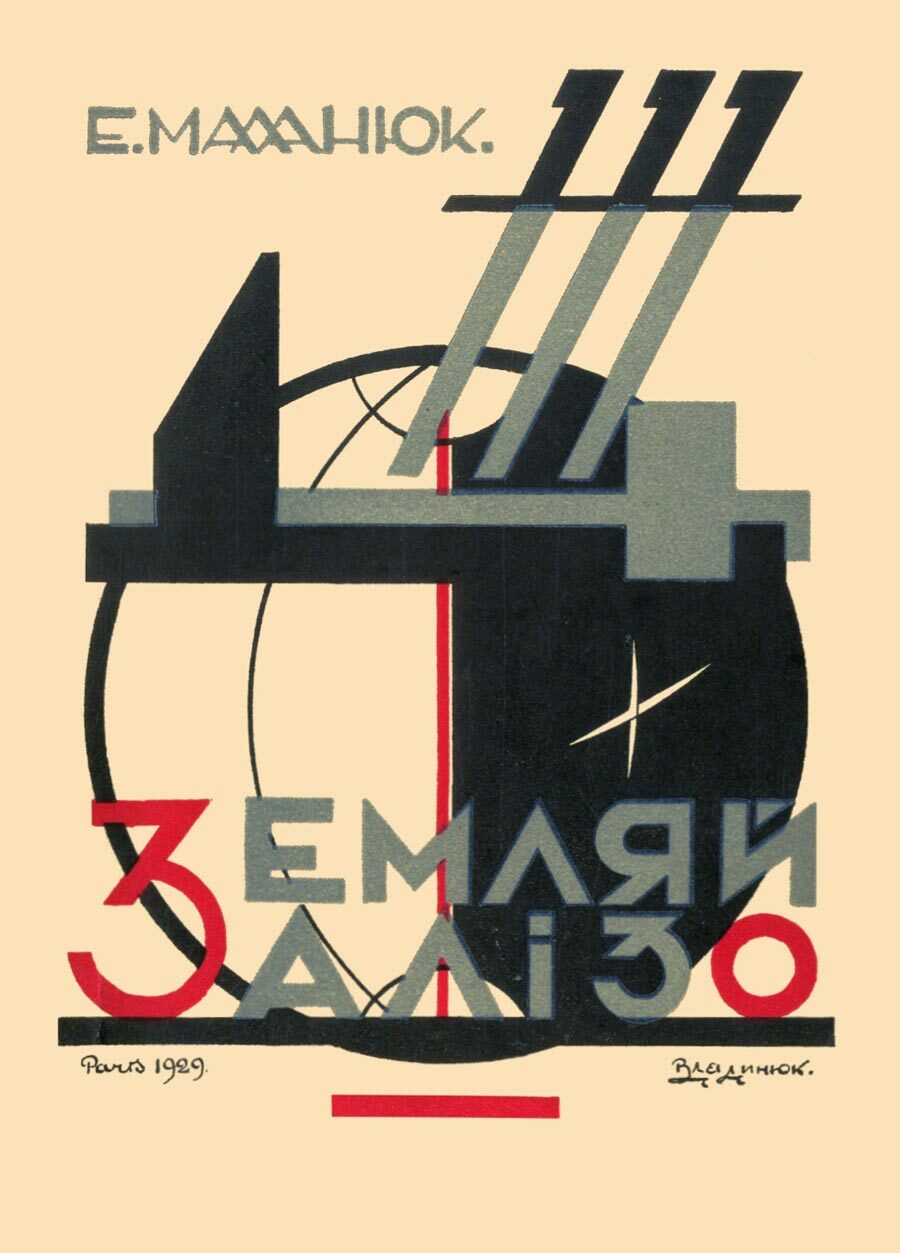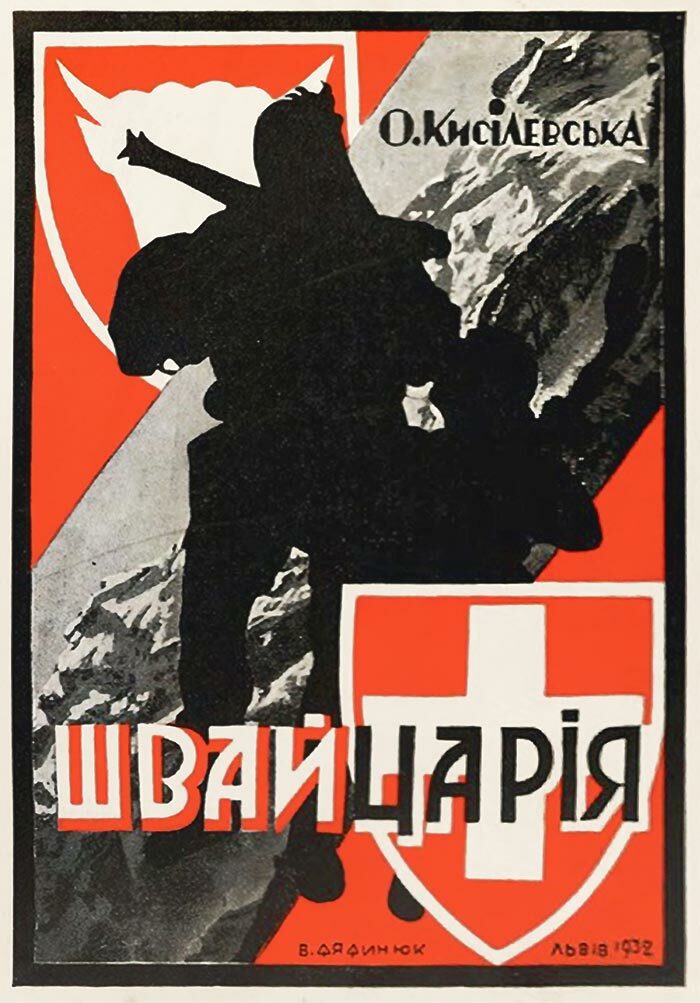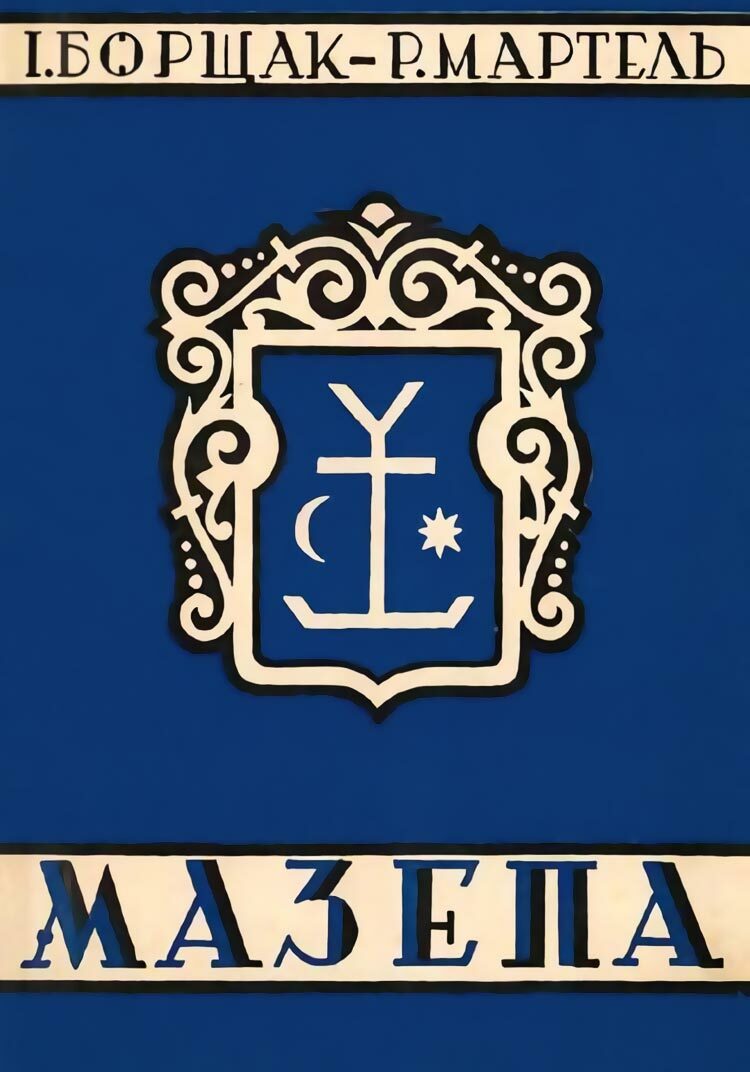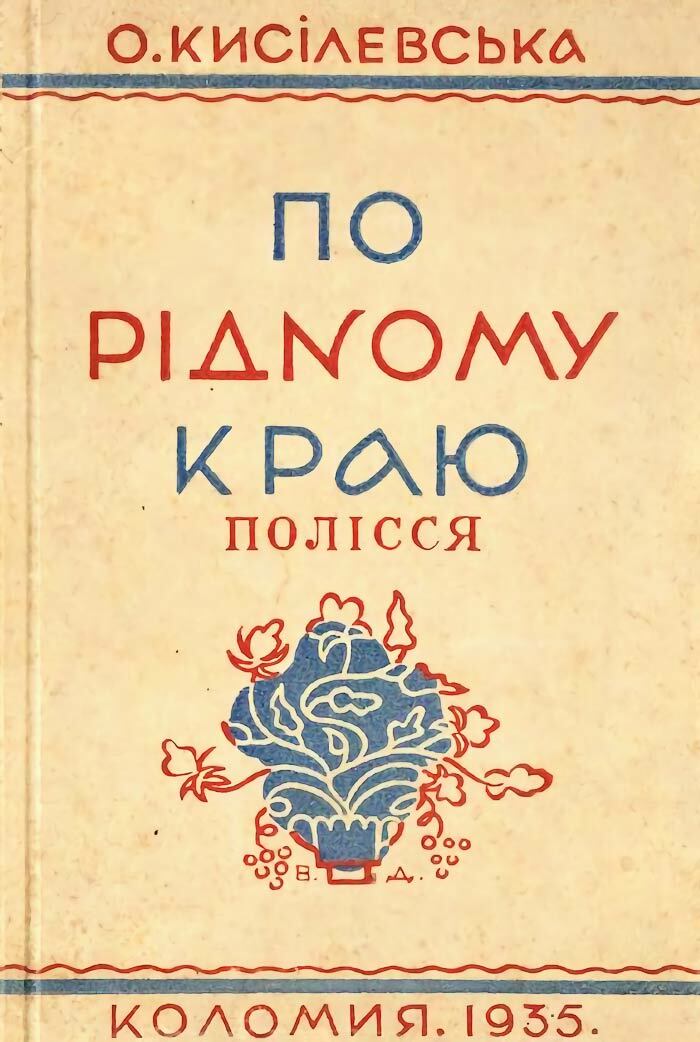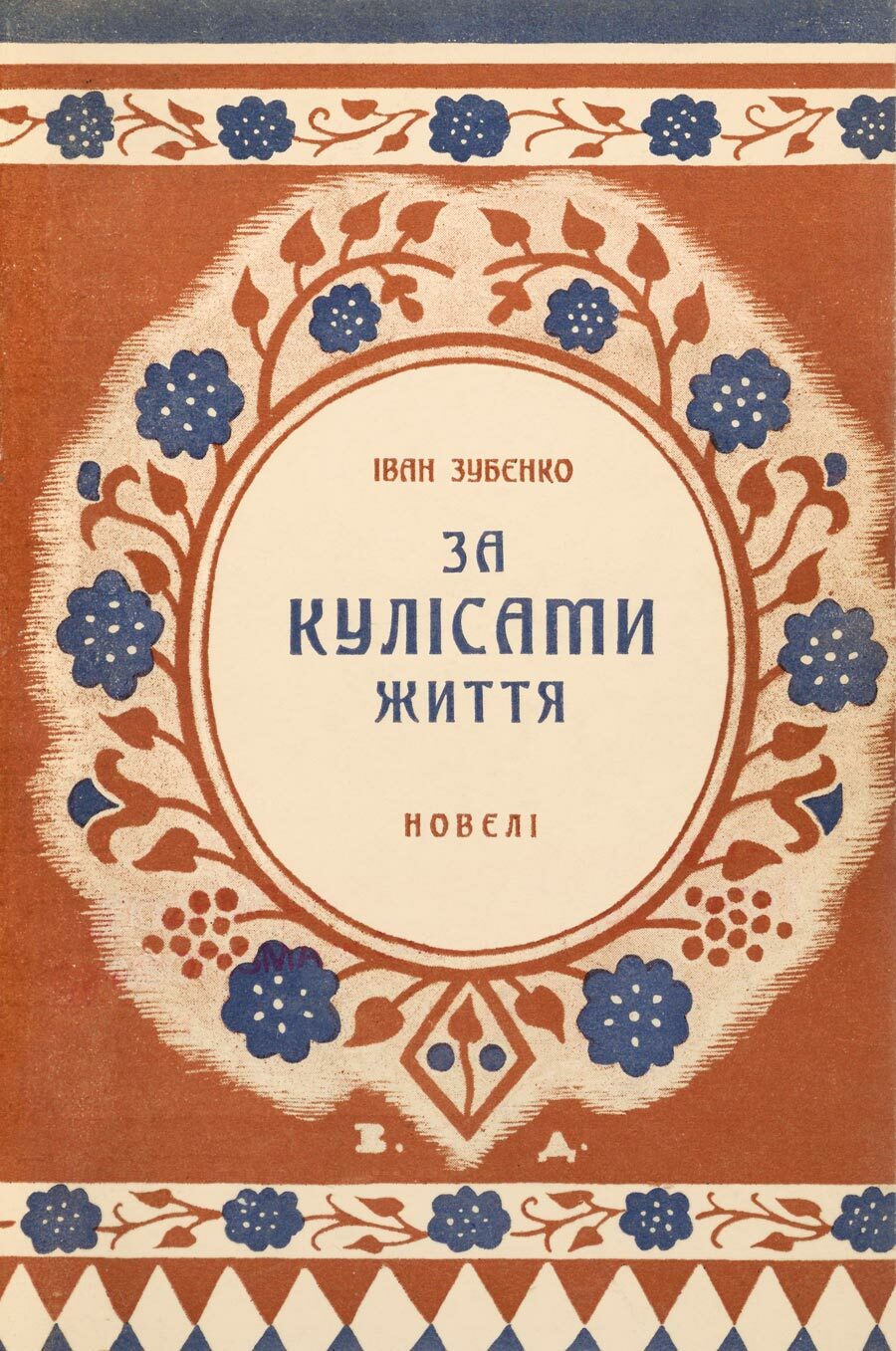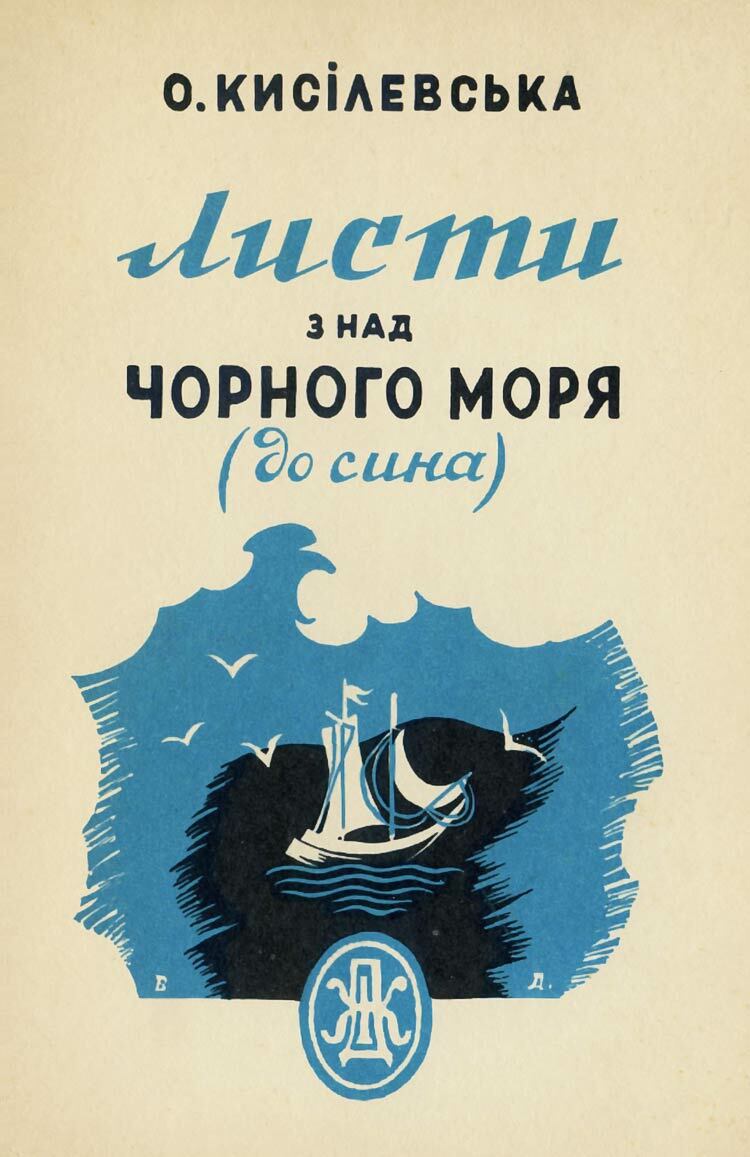
Василь Андрійович Дядинюк народився 1 січня 1900 р. у селі Лучинці Могилівського повіту на Вінниччині. Після закінчення середньої школи вступив до лав армії УНР, де дослужився до чину поручика. У 1920 р. опинився у таборі інтернованих у Калиші (Польща). Там активно працював над організацією мистецьких виставок, малював. У 1925 р. повернувся до Львова. Навчався образотворчого мистецтва в майстерні О. Новаківського. З 1926 р. по 1931 р. на замовлення Митрополита Андрея Шептицького копіював твори мистецтва у Вільнюсі, Дрездені, Парижі, Флоренції. У 1930 р. одружився з Ольгою Козакевич і певний час мешкав у Кракові. Впродовж 1930-1933 рр. керував школою релігійного мистецтва при одному з західноукраїнських монастирів. Здійснив кілька стилізацій в українсько-візантійському стилі, розписував церкви, займався книжковою та промисловою графікою. Виставляв свої роботи у Львові, Парижі, Варшаві. Був активним членом Спілки українських митців у Львові. Наприкінці війни разом із родиною опинився у Відні, де захворів і передчасно помер 21 січня 1944 р.
1939 рік
Книжкова обкладинка. Літерація, ілюстрація. Василь Дядинюк, 1939, Коломия.
1937 рік
Книжкова обкладинка. Ілюстрація, орнамент. Василь Дядинюк, 1937, Коломия.
1935 рік
Книжкова обкладинка. Літерація, ілюстрація. Василь Дядинюк, 1935, Коломия.